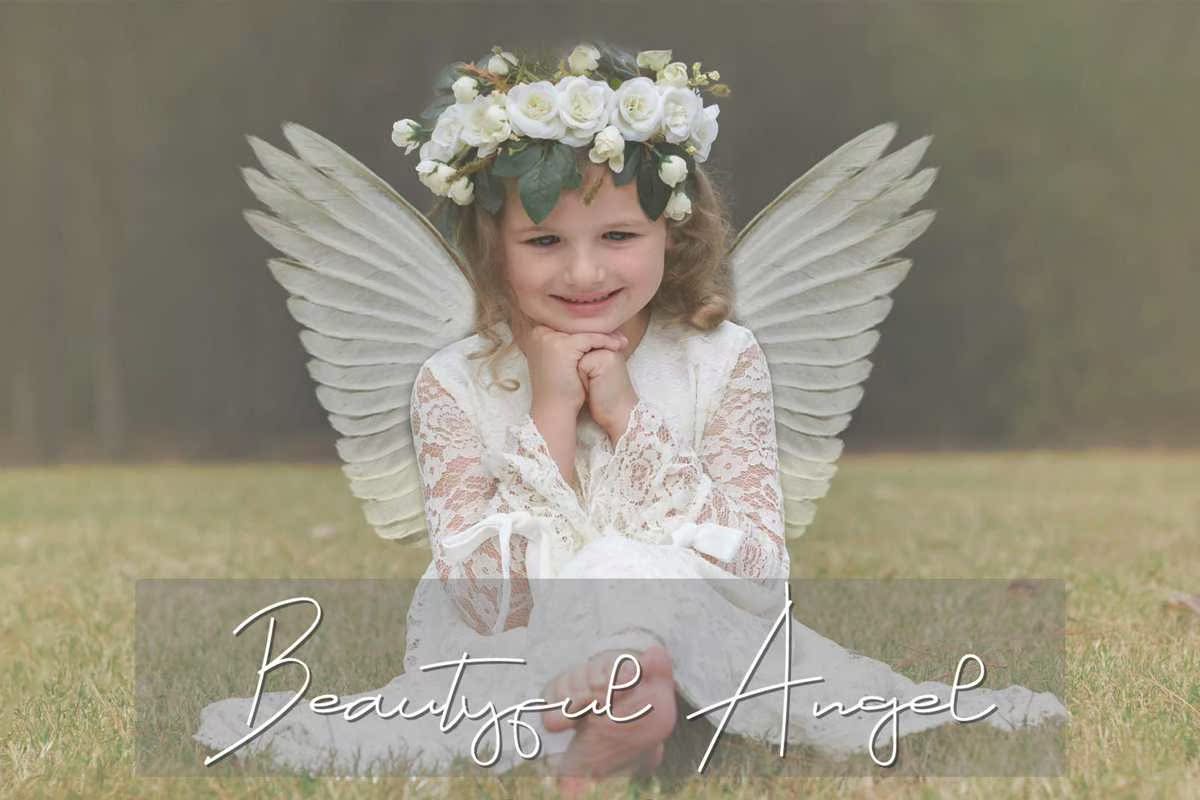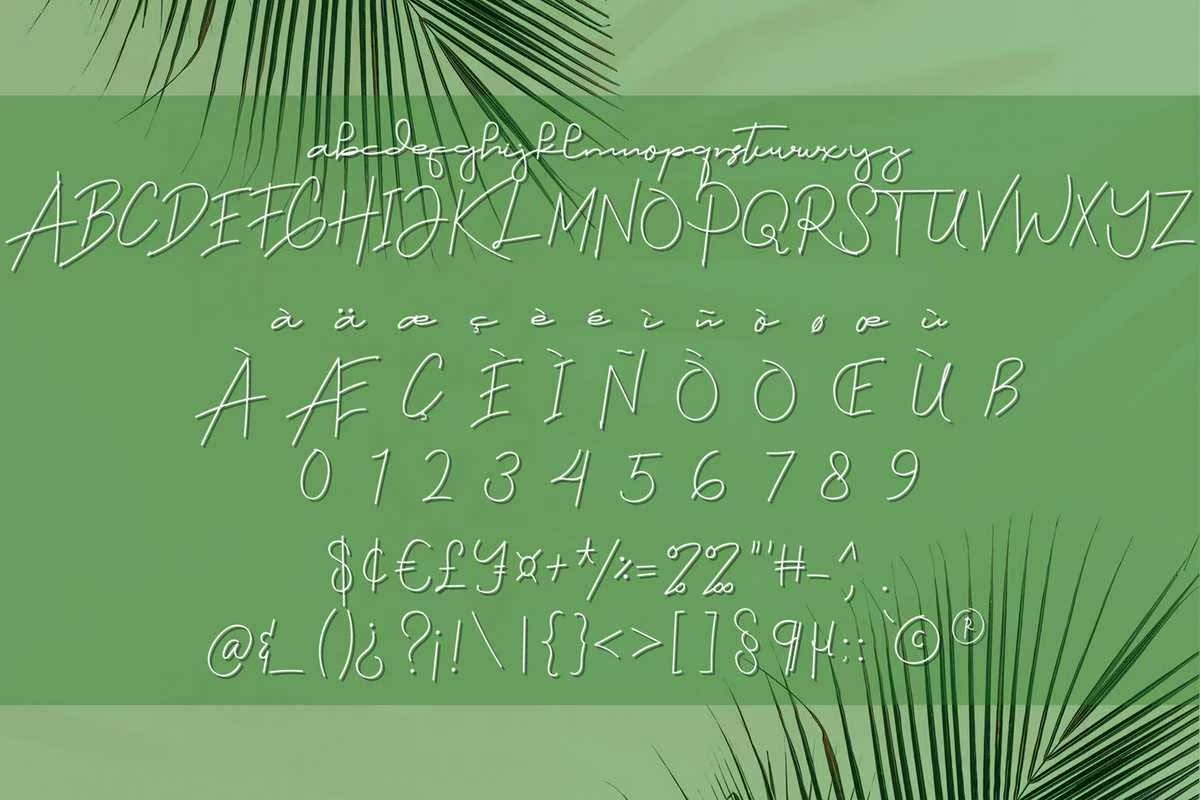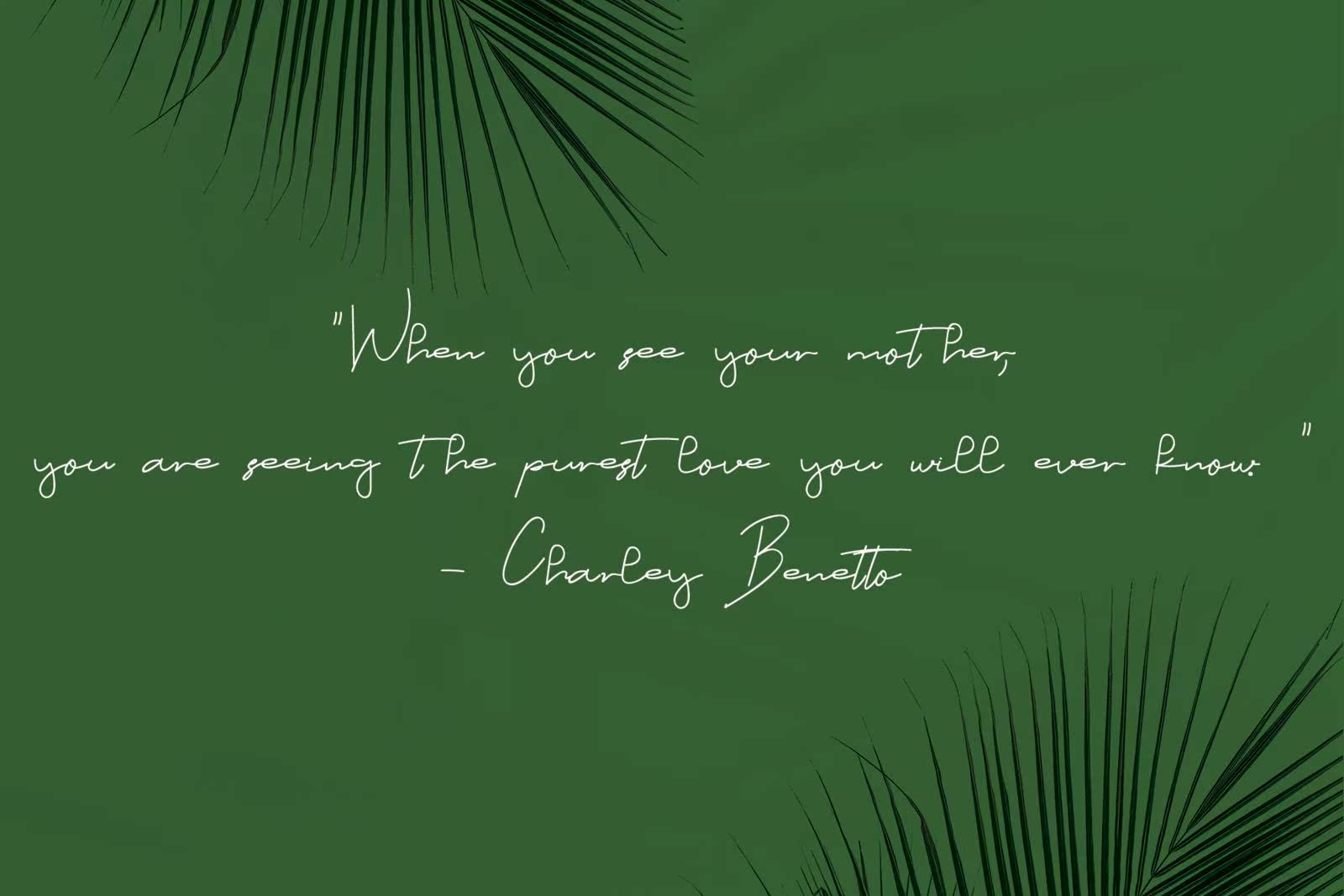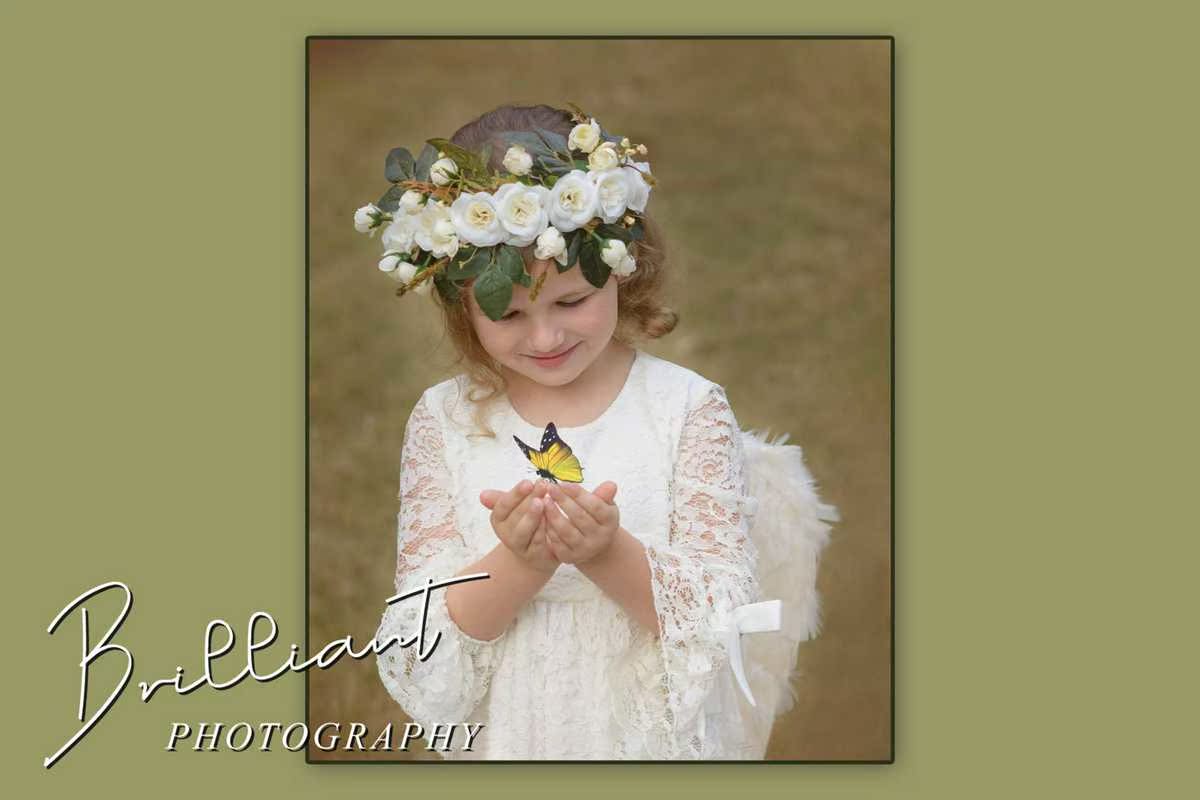
通过LegantTouch描述的AngelSignatures(天使签名)和Flowing(天使签名)以及WrittenFont(书写字体),完美地适合您喜爱的项目。这种优雅的风格将在各种设计理念中展现出来。它将为您的每一个项目增添更多乐趣和魅力!通过LegantTouch描述的AngelSignatures(天使签名)和Flowing(天使签名)以及WrittenFont(书写字体),完美地适合您喜爱的项目。这种优雅的风格将在各种设计理念中展现出来。它将为您的每一个项目增添更多乐趣和魅力!